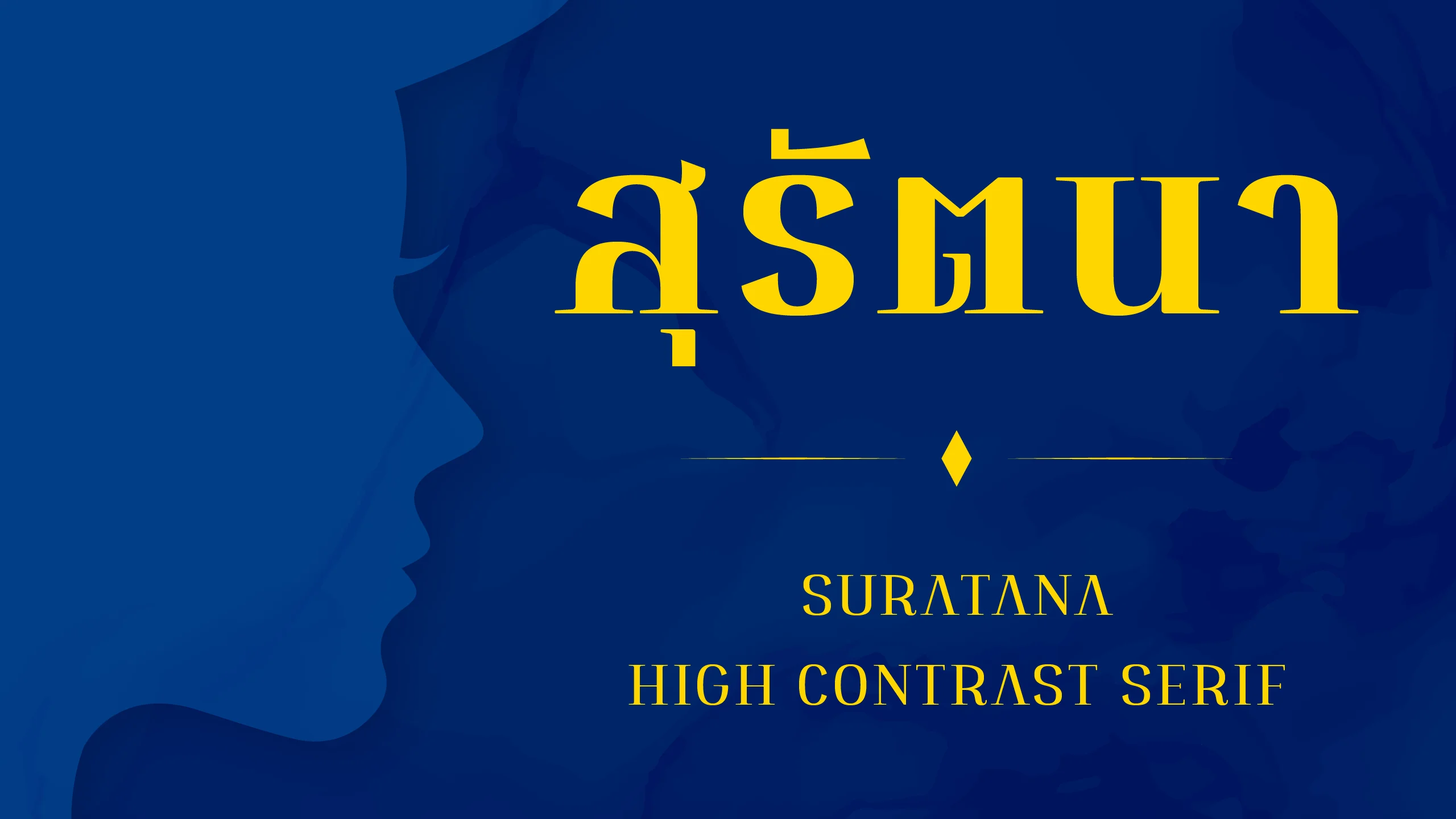
"สุรัตนา | SURATANA" คือชุดอักษรที่นิยามความหรูหราผ่านสไตล์ Serif ที่เปี่ยมด้วยเสน่ห์และรสนิยม โดยถูกออกแบบมาให้เป็นส่วนหนึ่งของโปรเจกต์ฟอนต์ฝาแฝดที่ใช้โครงสร้างอักษรร่วมกัน แต่มีการเติมเต็มรายละเอียดของหัวและปลายเส้นให้ดูภูมิฐานและคลาสสิก มอบบรรยากาศที่ดูเป็นทางการแต่ยังแฝงไว้ด้วยความละมุนตา สะท้อนความพิถีพิถันในทุกรายละเอียดการจัดวาง เพื่อยกระดับงานออกแบบของคุณให้ดูทรงคุณค่าและน่าเชื่อถือในทุกมิติ ด้วยดีไซน์ที่เน้นความประณีต "สุรัตนา | SURATANA" จึงเหมาะอย่างยิ่งสำหรับงานที่ต้องการภาพลักษณ์ระดับพรีเมียม ไม่ว่าจะเป็นงานสร้างแบรนด์แฟชั่น การออกแบบโลโก้ที่ต้องการความหรูหรา หรืองานกราฟิกที่เน้นความสง่างามสไตล์คลาสสิก โดยฟอนต์ชุดนี้จะทำงานได้อย่างไร้รอยต่อเมื่อใช้ควบคู่กับคู่แฝดในตระกูล ช่วยให้การสื่อสารในโปรเจกต์เดียวกันมีความหลากหลายแต่ยังคงความเป็นอันหนึ่งอันเดียวกันได้อย่างสมบูรณ์แบบ สุรัตนาไม่ได้มีเพียงมุมมองที่หรูหราเท่านั้น แต่ยังมี "ฝาแฝด" ที่สะท้อนความร่วมสมัยและสะอาดตา กับ "สุรัตนา แซนส | SURATANA SANS" ชุดอักษรโครงสร้างเดียวกันที่ตัดทอนจนเหลือเพียงความเรียบเท่ เพื่อการใช้งานที่หลากหลายและสมบูรณ์แบบยิ่งขึ้น